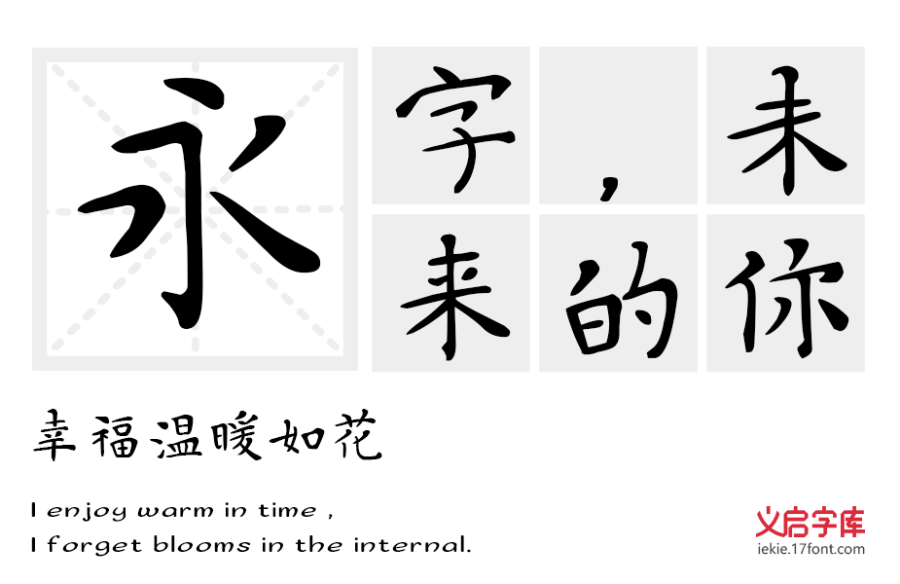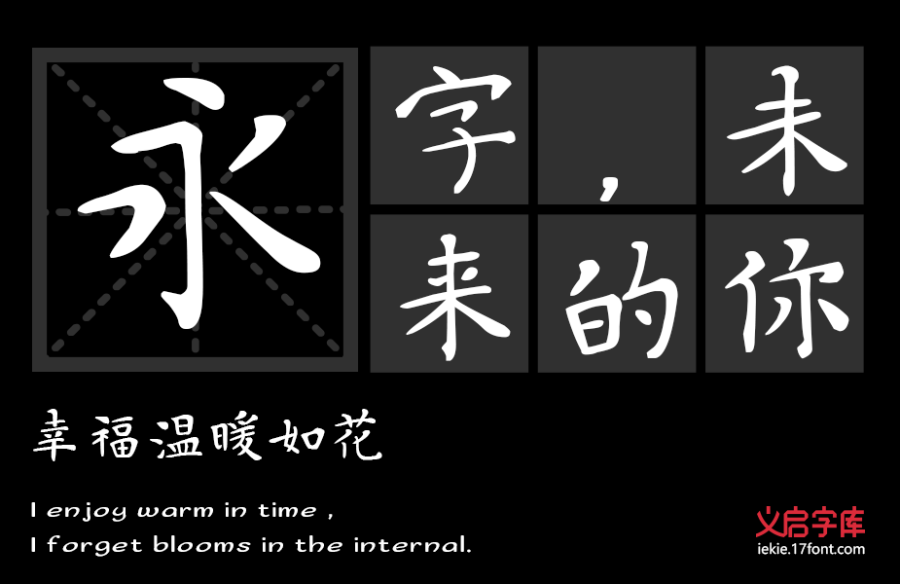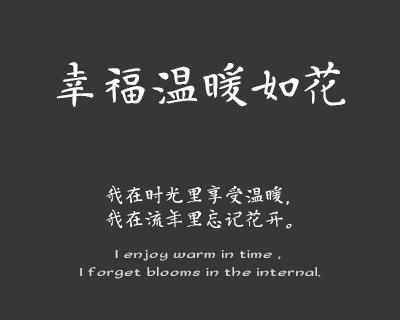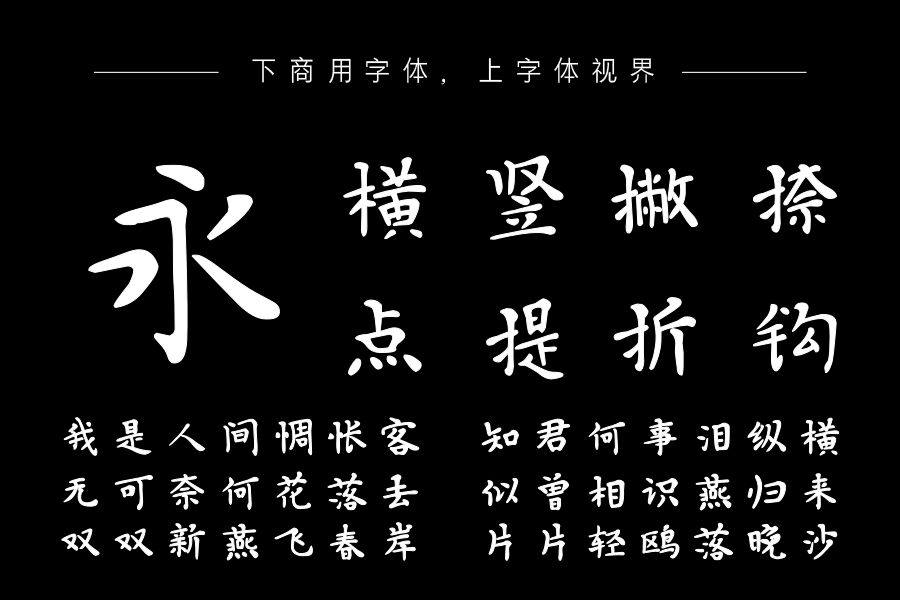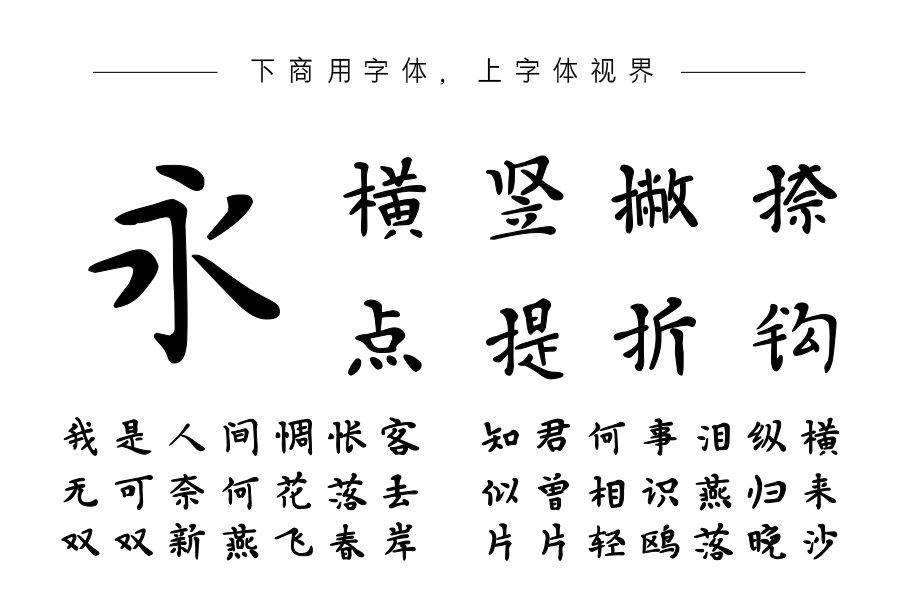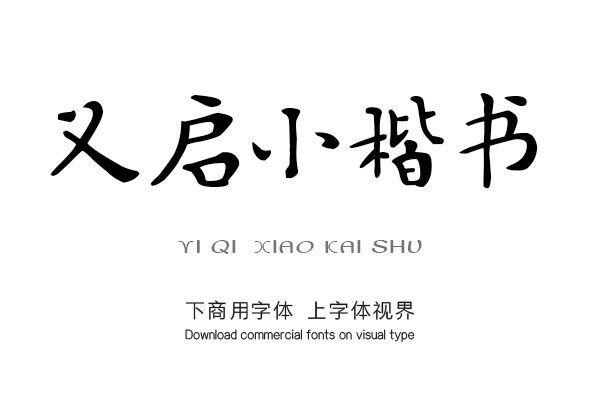
小楷,即是楷体小字。 义启小楷书,是一款汲取历代小楷特质为基础的书法字库。而从现实效果上摆脱了书法字库在小显示屏上的弊端,主要在笔画上做了改善。小楷的灵魂在于“小字如大字 ”,就是字小要有大字的气象与章法。修饰笔画在保证气象的基础下,变的圆润简洁,不至于显示时出现不了效果反而糊掉。结构上收放有度,气势如虹。章法更是左右衔接,一气呵成。分享到